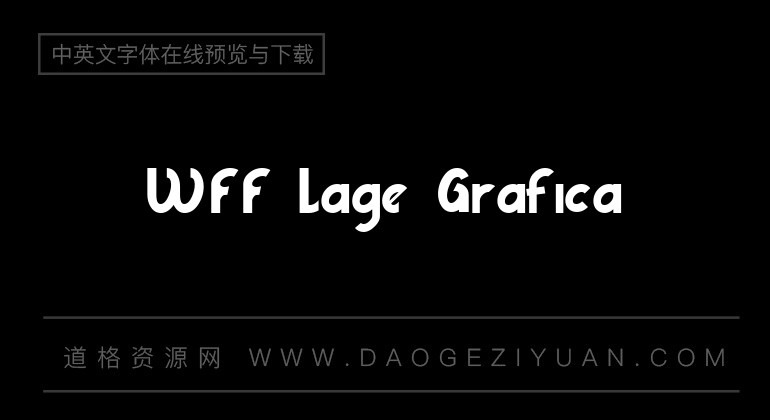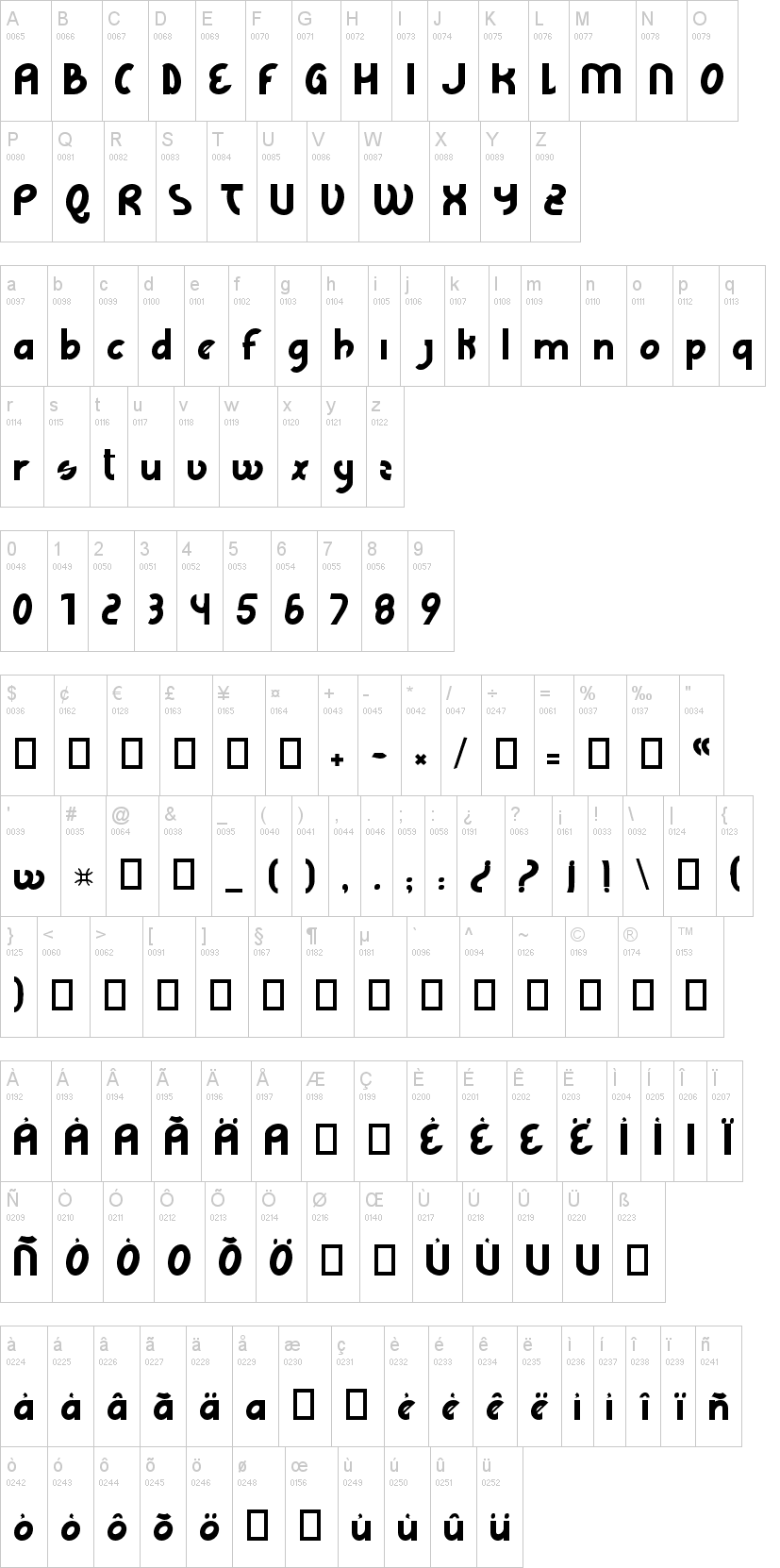
WFF Lage Grafica
WFF Lage Grafica是一种现代风格的无衬线字体,设计于2010年。该字体由位于谷歌公司的字体设计师Wei Huang设计,其设计理念是为数字和网页设计而创建一种简洁、清晰的字体。 WFF Lage Grafica字体的特点是字母的笔画流畅,字形简单,线条粗细均匀。它的设计灵感来自于工程和建筑图纸上使用的曲线和角度,因此它的字形看起来非常结构化和现代化。 该字体适合用于大字体、标题、标语等场合,能够增强设计作品的现代感和专业感。WFF Lage Grafica字体提供了多种字重和格式,可供选择使用。
WFF Lage Grafica是一款非常不错的手写艺术字体,具有很好的视觉感,适合于文化类的宣传设计、商业类品牌的广告和产品包装设计以及个性化文字排版等较多场景。
WFF Lage Grafica字符映射图